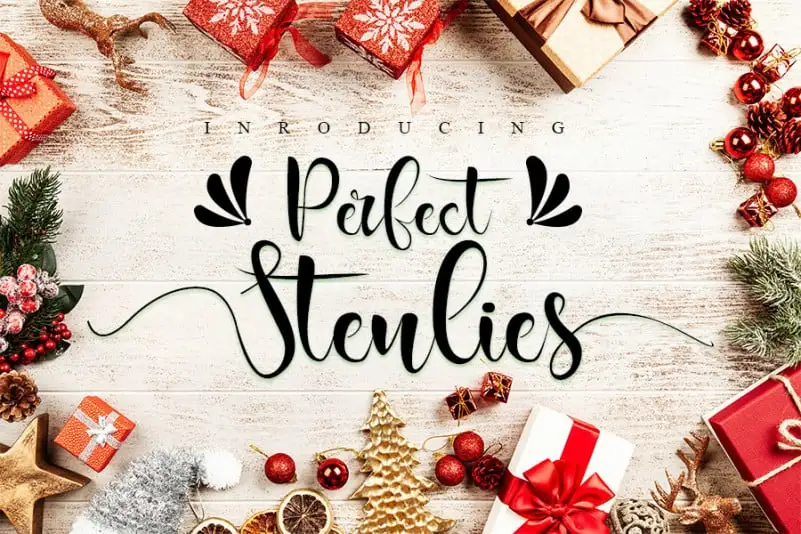
Perfect Stenlies Calligraphy Font – Download Grátis
A fonte “Perfect Stenlies Calligraphy Font” é uma escolha excepcional para quem busca tanto estilo clássico quanto atualidade fresca e inovadora. Com um caráter script, ela mantém seus influentes traços de escrita artesanal enquanto oferece um toque contemporâneo que vai além da simplicidade tradicional. Suas capacidades versáteis a tornam perfeita para uma variedade vasta de propósitos criativos, desde os logotipos e cabeçalhos até as embalagens e cartões de papelarias. Ideal tanto para aqueles que buscam um design elegante quanto para quem deseja incorporar novas ideias em suas criações. A “Perfect Stenlies Calligraphy Font” é uma escolha inteligente para qualquer projeto que valorize a estética clássica revigorada com um toque moderno e atual.